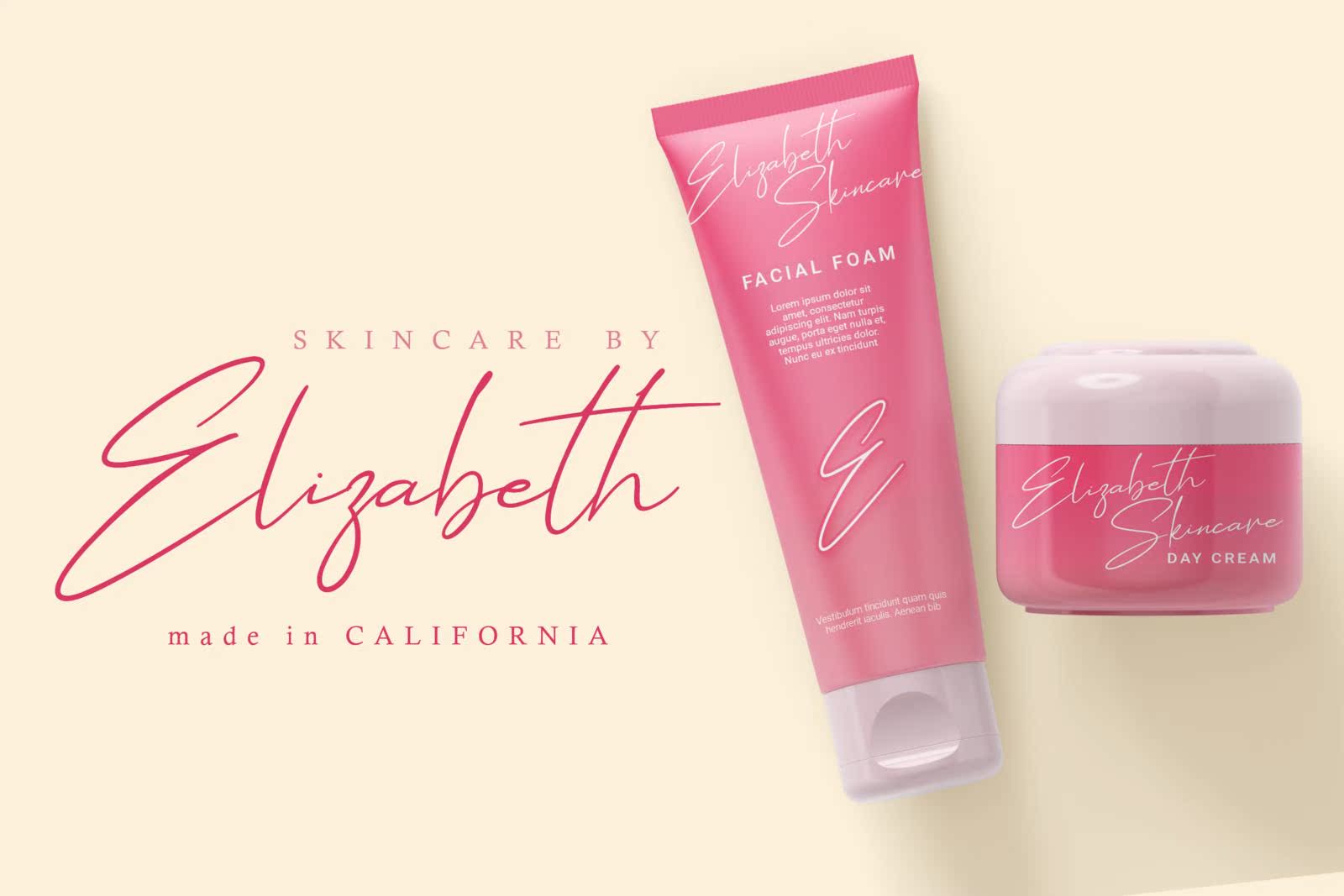
Hathem Bostee误解了时尚签名样式脚本,使其看起来优雅、优雅、流畅、时尚。该字体创建的目的是使其成为接近自然和书写的脚本。Hathem Bostee对品牌项目、徽标、婚礼设计、社交媒体、广告、产品包装、产品设计、标签、照片、水印、邀请、,文具商和需要手写品味的项目。Hathembostee对时尚签名样式脚本的误解使其看起来优雅、优雅、流畅、时尚。该字体创建为一种接近自然的书写脚本。Hathembostee是品牌项目、徽标、婚礼设计、社交媒体、广告、产品包装、产品设计、标签、,照片、水印、邀请函、文具和需要手写的项目。